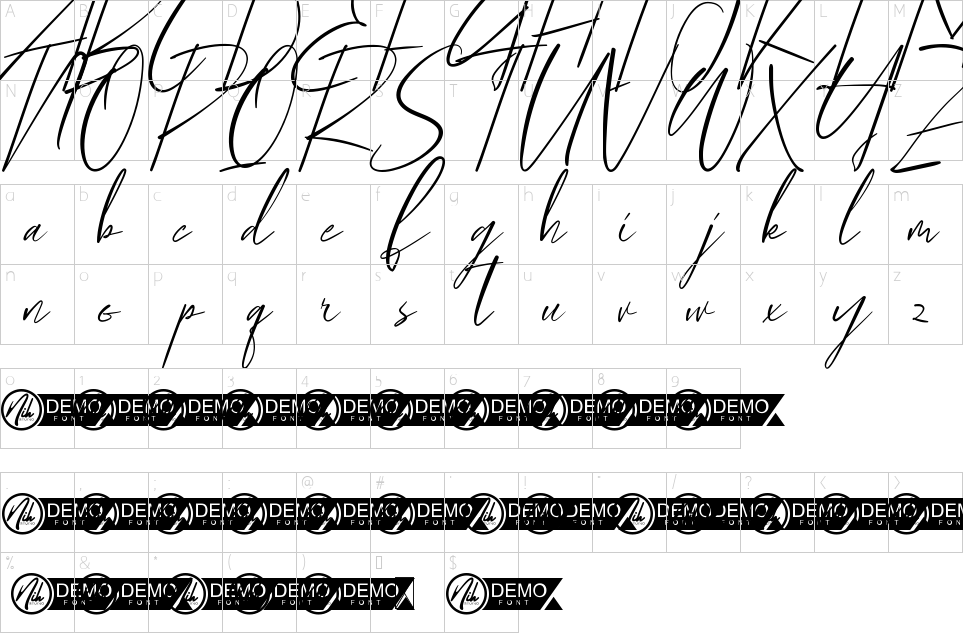
A Geofanny Jania é uma fonte livre que oferece um equilíbrio entre modernidade e elegância. Desenvolvida pela NihStudio, esta fonte pode ser baixada tanto para sistemas Windows quanto para Mac. Com seu design minimalista mas detalhado, a Geofanny Jania é ideal para uso em projetos de design gráfico que requerem um tom sóbrio e confiável. Possui uma facilidade de leitura alta, garantindo que o texto seja visível mesmo em formatos maiores ou mais próximos ao olho do espectador. Seja você um designer profissional ou iniciante, a Geofanny Jania é uma fonte versátil e prática para sua biblioteca de recursos gráficos. Com seu design limpo e funcional, ela está aqui para complementar o seu trabalho.